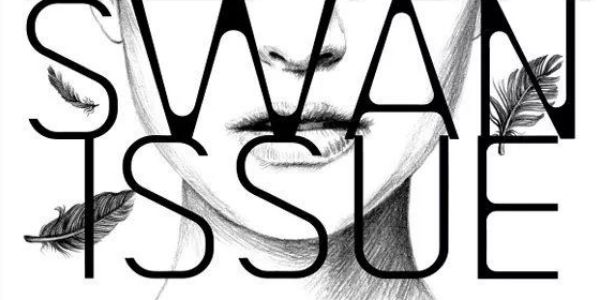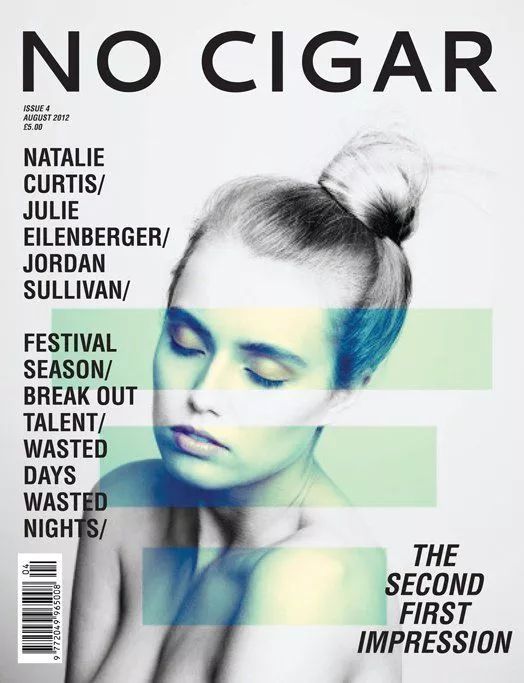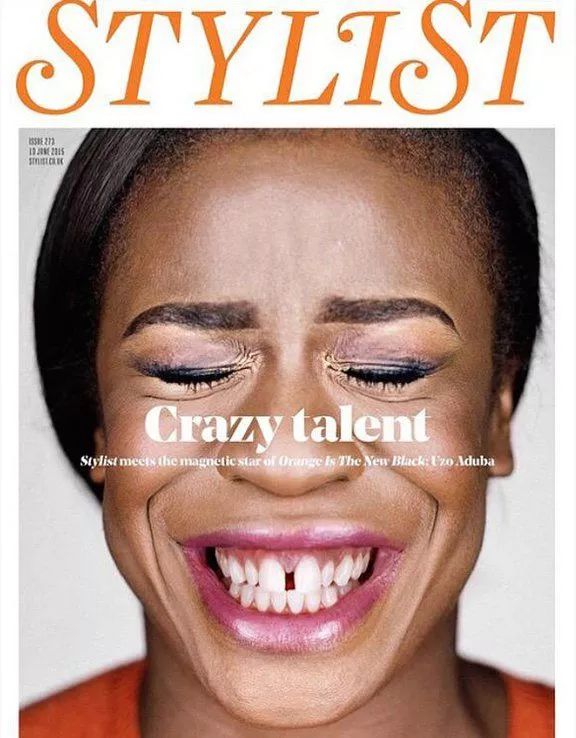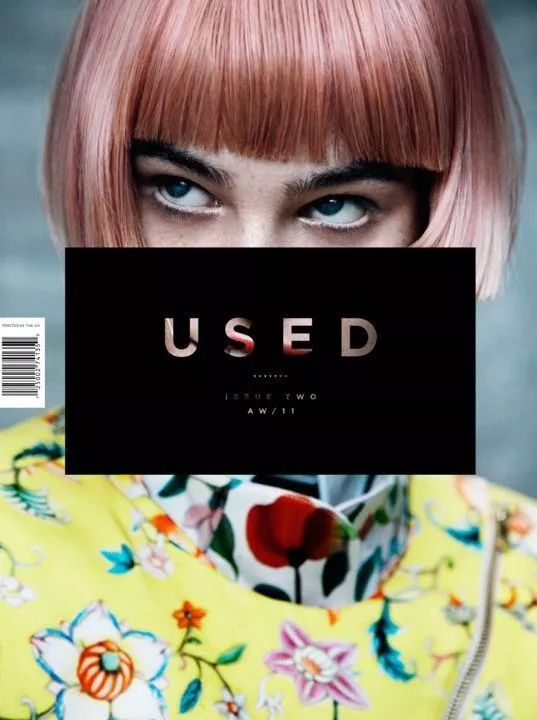
对杂志而言,封面设计承载着两个重要目标:一是吸引潜在读者的注意力,另一个则是表达主题。只有充分做到这两点,才能刺激消费者的购买欲。我们研究比较了各类杂志封面设计,选取了50个引人注目的案例,希望通过介绍这些设计理念和技巧,帮你了解如何快速捕捉注意力。
将标题放在显眼位置
Little White Lies, Jan/Feb 2011
内容标题在Little White Lies封面上占据了主要位置,甚至比刊名更加显眼。娜塔莉波特曼的脸上露出黑色挫败的图案,大胆地宣称“黑天鹅问题”。
翻转布局
Blend, May 2011
这期Blend使用经典的布局翻转设计技巧,它以背景为中心,发布标题和设置边缘图像,十分引人注目
使用单点透视构图
New York Times Magazine, 29 December 2013
封面是詹姆斯·甘多菲尼(James Gandolfini)饰演的凯迪拉克敞篷车,主题为“他们生活的生活(以及他们喜欢的事物)”。汽车和副标题的角度,位置和大小创造了一个消失在距离中的单点透视。
创造一个激光切割封面
Audobon, May/June 2014
Columbus Monthly使用激光切割街道地图制作“哥伦布制造”杂志,由哥伦布当地公司设计和制作。在粉红色的背景上覆盖灰色激光切割增加了阴影和对比度的维度。
展示一个序列
Audobon, May/June 2014
Audobon的封面使用网格来显示由 John Huba拍摄的Roseate Spoonbill优雅的飞行顺序。它展示了鸟类的颜色和飞行状态,并采用极简主义排版对齐以加强网格。
合并图像与背景
Naif
女孩的油亮黑发与黑色背景在Naif的封面上融为一体,白色的头花和粉红色的脸颊为整体增添了一丝色彩。
使用具有冲击力的图像
Stylist, June 2015
Martin Schoeller在2015年6月的造型师封面上拍摄了Orange Is the New Black女演员Uzo Aduba。Aduba的眼睛紧闭着,咧嘴大笑,她的表情充满着快乐和喜悦,富有吸引力。
尝试透明图案
No Cigar, August 2012
这款No Cigar封面在一张沉思的模特照片上使用了简单的透明胶块。这三个透明胶片可以增加色块,同时不会破坏封面模特的情绪。
玩转面部彩绘
Vogue
Jessica Fecteau用大胆的线条和角度创造了这款Vogue封面。红色和青色的线条穿过模特的脸部和手部,和刊名相互交映。
运用剪纸艺术
Washington Post Magazine, 23 December 2012
Ariane Spanier在封面上创造了一种用切片和螺旋纸组成的粗体字母,以表达该杂志主题——“Lives Remembered”(讲述2012年去世的人们的生活故事)
大胆运用漂亮和甜美因素
L’ode
在杂志封面的世界中,一种漂亮而甜美的审美往往与众不同,其中大胆引人注目。
但是在设计学生朱莉·费里厄(Julie Ferrieux)展示的L' Ode封面上,优雅的植物群展示似乎漂浮在整个页面上也很引人注目。
用刺绣创造质感
Desktop, No. 299
设计工作室Maricor / Maricar用刺绣赋予封面质感和立体感,并通过将民间艺术翻译成数字艺术来说明杂志的主题。
避免眼神接触
Lovely, Spring 2014
虽然在大多数杂志的模特都会与读者眼神直接接触,但Lovely封面的模特避开了眼神接触,为画面增加了诡诈和偏心。
假光源
Print New Visual Artists, 2015
Shane Griffin设计了2015年Print New Visual Artists的封面,他在背景上使用了渐变,使光源的外观触及右上角,为封面增添了一种立体感。
尝试迷幻色彩
Volt, No. 19
插画家Matt Corbin使用明亮的迷幻色彩和类似小球的形状,营造出一个坚强的女性形象,背景是闪亮的黑色背景。
使用夸张放肆的照片
Surf
Surf的封面上一个小男孩在镜头前伸出舌头,人们很难不被它吸引。用Wedge&Lever的话来说,“复杂性并不会让人过于认真“。
将刊名放置于中心
Pilot, Issue 3
由Jase Mildren设计的Pilot的这个封面,使Pilot名称居于杂志中心,模特从后方直视这个刊名。
创造撕裂感
Wad
Wad的这个封面使用了模特脸部撕成两半的幻觉,露出了她脸上的另一个形象,也许模特是被困住了,也许是她被赋予了凝视读者的权力——画面中三只眼睛盯着潜在的读者。
使用简单的线条和表格
LiceUlice, Issue 24
LiceUlice的封面是由具有一个面部轮廓和一个握紧的拳头组成,表明杂志给街道上经常看不见的面孔带来的力量。非常简单的线条,形式和颜色营造出醒目的形象和强烈的声明。
使用条形码传达内容
a Luna de Metrópoli
La LunadeMetrópoli的封面在条形码中插入了9月11日袭击世界贸易中心的插图。
添加透明覆盖膜
well
Sidney Lim使用了带有笔刷桅顶的透明覆盖物作为他的Dwell封面。白色标志就像一朵云,当透明度移动时,它会在天空中投下阴影。
使用一系列简单插画
Odd
Odd的封面将简单的插图,最小的调色板和白色背景结合在一起。Miriam Garcia创造了一系列游泳运动员,使其毫不费力地漂浮在整个页面上。
使用金箔纸反射光线
Slanted 25
Slanted 25封面被金箔覆盖,并印有重复的图案,随着光线闪烁为封面增添了几分魅力。
将模糊图像与清晰线条对比
Little White Lies, Jan/Feb 2011
平面设计师David Carson在Ray Gun的这个封面上,覆盖了一个模糊的,几乎是潮湿的Beck图像,带有强烈的黑色排版,使得每个字母的孔都更加大胆。
使用极端特写
Fricote, Issue 3
这款Fricote的封面是一个红唇,嘴里叼着被冰覆盖的覆盆子。有光泽的嘴唇和闪亮的冰块成了提升这个封面的高端因素。
实验室风格
Little White Lies, Jan/Feb 2011
这个封面的标头中的一个细长的O从页面的顶部延伸到底部,一直循环向上。它将标头与图像连接起来,并为要对齐的杂志的细节提供一条线。
背离超现实主义
Magrocardona
Magrocardona的封面图像中,模特的上躯干和下躯干朝着两个方向行走,模糊了人们的视线方向。
与传统工具相结合
Little White Lies, Jan/Feb 2011
Adbusters封面的艺术构图回到了传统的艺术工具箱,玩转串通的绘画媒介——油漆,蜡笔,粉彩,铅笔。
遵循一个版式
Gist
由墨西哥代理商Anagrama设计的Gist的封面都遵循一个版式:在模特的肖像上添加闪亮的箔边框。这个封面依旧坚持了这个模式,在奢华的黑白图像上使用鲜红色的框架。
30
使用超宽框架
Spleen
Spleen的封面使用了一个超宽的框架加上一个小图片,将杂志的标题,发行号和主题都放在边缘,吸引人们注意中央图像。
31
棕褐色调的怀旧情怀
Feld
Feld封面上包含许多有趣的设计技巧,包括块状排版,透明度和古怪的图像。所有因素都以棕褐色调呈现,给人一种怀旧的感觉,同时仍然具有鲜明的现代感和现代感。
32
变形图像
Exhibition
在这个封面上这个模特的脸看起来是变形和呈现滴落状况。然而,仔细观察,你会发现它实际上是一条披在模特脸部和躯干上的真丝围巾。
33
使用框架突出重点
Hen Magazine
一条脱节而破碎的白色线条勾勒出Hen杂志封面上的模特的嘴,它突出并引起人们对她厚颜无耻的冷笑的注意。
34
使用几何透明度增加深度
Myp
Myp是一个在线杂志和设计项目,展示了年轻创意人和艺术家的作品。这个封面在图像上放置具有不同透明度的几何图案,为图像增加了不同的深度。
35
注重景深
Pedal
Pedal的封面使用浅景深拍摄一张男人的照片,这张照片越来越深入到水中,以便产生一种渴望和冒险的感觉。
36
捕捉动态运动
U/C
U/C的封面是一个舞者被一群其他舞者抛出或抓住的动作的动态图片。图片是在舞者伸展的四肢的动态张力中捕捉到的。
37
探索负空间
Used
Used封面通过从页面中心的实心黑框中切割标头来探索负空间。通过负空间可以看到模特脸部的一瞥,模特的眼睛和她的发型被黑匣子框住,引人遐想。
38
创造匿名感
BEople, Issue 1
比利时杂志BEople在页面中间的模特脸上使用了白色的圆圈,以创造匿名感破坏模特和观看者之间的联系。
39
遵循一个版式
Thursday
封面由白色图案组成了负空间,主要的图像是金色和棕褐色,以此突出了“爱”的主题。封面整体呈现浪漫和多愁善感的感觉。
40
最大化空白
Human Being Journal, April 2013
Human Being Journal的封面有大量的空白空间,框架上有桃红色的边框,它反映了“少即是多”的设计原理,并且与任何复杂的封面图像一样引人注目。
41
考虑不同拍摄视角
Soccer
Soccer的封面是一个男孩在平衡他头上足球的照片。照片视角是从下往上拍摄,照片增强了男孩的存在,并在页面顶部创建了一个消失点。
42
使用暖色调
Esquire
Esquire的封面中一对夫妇在海滩上亲吻的照片浸透在温暖的黄色光晕中,突出了夏天的炙热感。
43
创造剪影效果
Dallas Observer
Dallas Observer封面上是一个穿着印第安原住民头饰的男人的轮廓和他脸上的阴影。
44
在形状内放置图像
Brownbook No. 40
Brownbook在白页上的六边形内策略性地放置了模特,使她的头部和脚趾到达六边形的顶角和底角。
46
添加一种流行色
L'Insensé
L'Insensé封面的顶部,中部和底部都有鲜红色的流行色,并且有趣的是他们将观众的目光吸引到模特的眼睛上。
47
用色彩营造情绪氛围
Influencia
设计师Violaine和Jérémy使用柔和而微妙的色彩,在画面中间放置一杯飘着蒸汽的茶,营造出一种轻松的氛围。
48
创建撕纸的图层
Clash
在这个Clash封面使用撕裂的纸条的假象来揭示每个面的不同部分,创造层次感。
49
找到引人注目的视觉效果的图案
Makeshift
Makeshift的封面上有一张照片俯拍角度拍摄的照片,照片中的人物重复着同一个动作,创造出一种惊人的视觉效果。
50
使用手绘技术
Yorokubu
Vicent eGarciía Morillo使用铅笔和口红来制作Yorokubu的封面。他用铅笔画了一个嘴唇插图,并用口红画上了四个不同的字母。